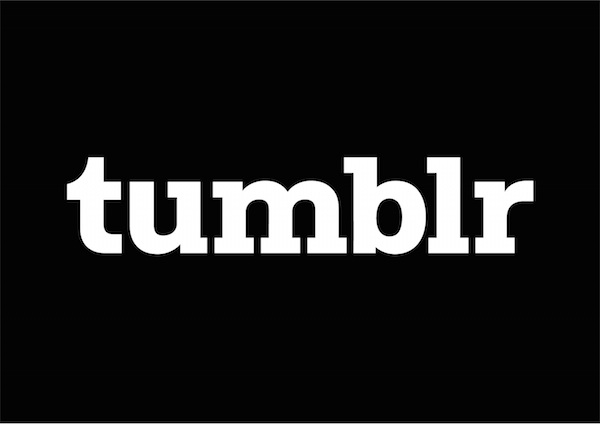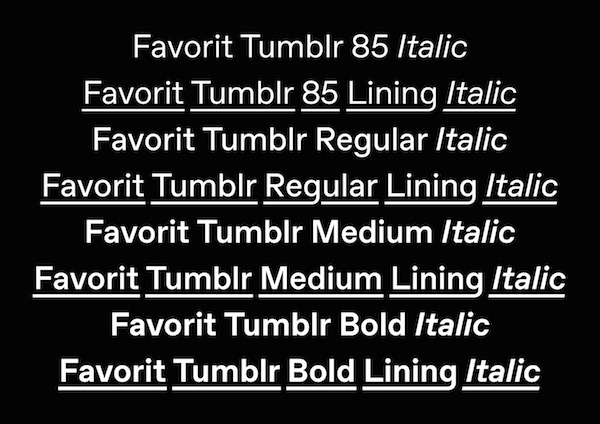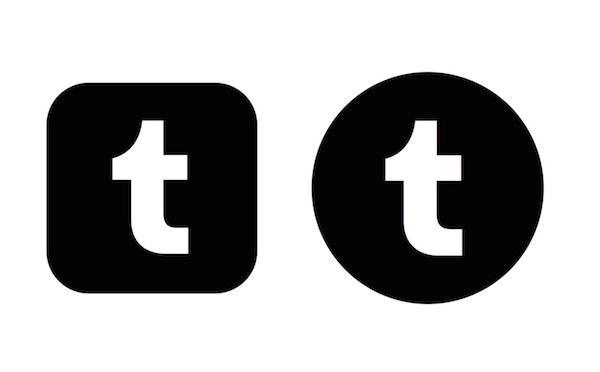
Tumblr presenta su nuevo logo y tipografía
Nuevo logo y tipografía de Tumblr
Con el tiempo las marcas y redes sociales tienen que renovarse para no morir en el mundo del Internet; es por ello, que Tumblr ha rediseñado su imagen por una más atractiva y ordenada a la vista.
Aún cuando Tumblr ha sido superada por Pinterest en algunos aspectos sigue teniendo presencia; es por ello, que no se han dormido en sus laureles y presentan su nuevo logotipo ajustado a su nueva tipografia basada en su favorita: la “favorit” y que recibe el nuevo nombre de “Favorit-tumblr”.
Nuevo logo y tipografía de Tumblr
“equilibra con éxito los atributos básicos de sans serif con una geometría asertiva y contemporánea” – señala DougRichard director creativo de Tumblr.
Por lo anterior, es necesario manifestar que este nuevo diseño ha sido creado en asociación con la firma de diseño DINAMO; explicando que la visión de esta agencia ha derivado en un rediseño más atractivo pero discreto de las letras “T” y “R” del mencionado logo para darles mayor presencia y elegancia con un nuevo porte.
Además, este re-diseño ha eliminado el “.” al final del logotipo; algo que fácilmente puede pasar desapercibido.